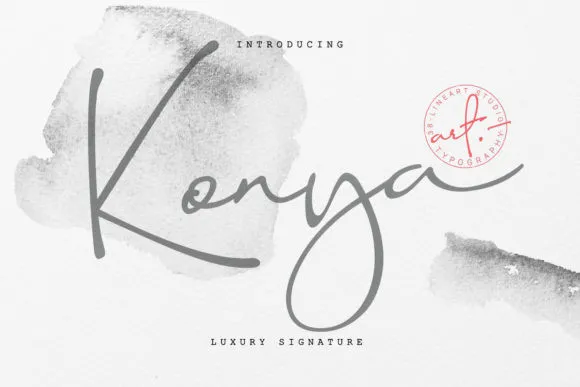
Konya Signature Font
A Konya Signature Font é uma elegante escolha para aqueles buscando um estilo personalizado e sofisticado em seus projetos gráficos. Com suas traçadas cuidadosas e sua aparência natural, essa fonte de script escrevendo à mão oferece uma opção única que adicionará um toque pessoal a qualquer projeto. As alternativas de caracteres presentes na fonte a tornam ainda mais versátil e adaptável às necessidades específicas do design. Com seu olhar delicado e sua sensibilidade, Konya é perfeito para aqueles buscando dar um brilho luxuoso à sua arte digital. Esta fonte se assemelha muito à uma assinatura autêntica, fornecendo um toque único que certamente impressionará seus destinatários. Seja você criando cartões de aniversário ou publicidades para sua marca, a Konya Signature Font traz um aspecto sofisticado e ímpar ao seu trabalho. Seja você uma designer gráfica profissional ou um aspirante à arte digital iniciante, esse script de escrita à mão é uma fonte que vale cada centavo.